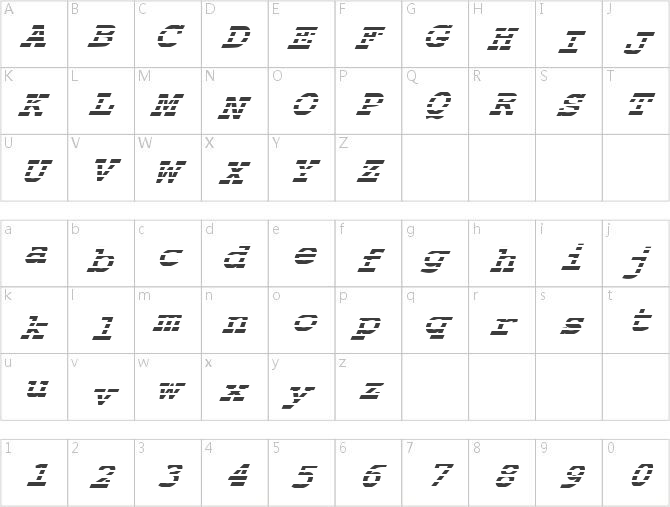
FZ BASIC 54 STRIPED ITALIC 詳情頁(yè)
FZ BASIC 54 STRIPED ITALIC字體字庫(kù)是一款讓人賞心悅目、百看不厭的英文字體,適合各類(lèi)廣告和產(chǎn)品包裝設(shè)計(jì)應(yīng)用,字體大小0.06MB,格式為ttf字體,上傳用戶是錦程正陽(yáng),作者/版權(quán)方為未知